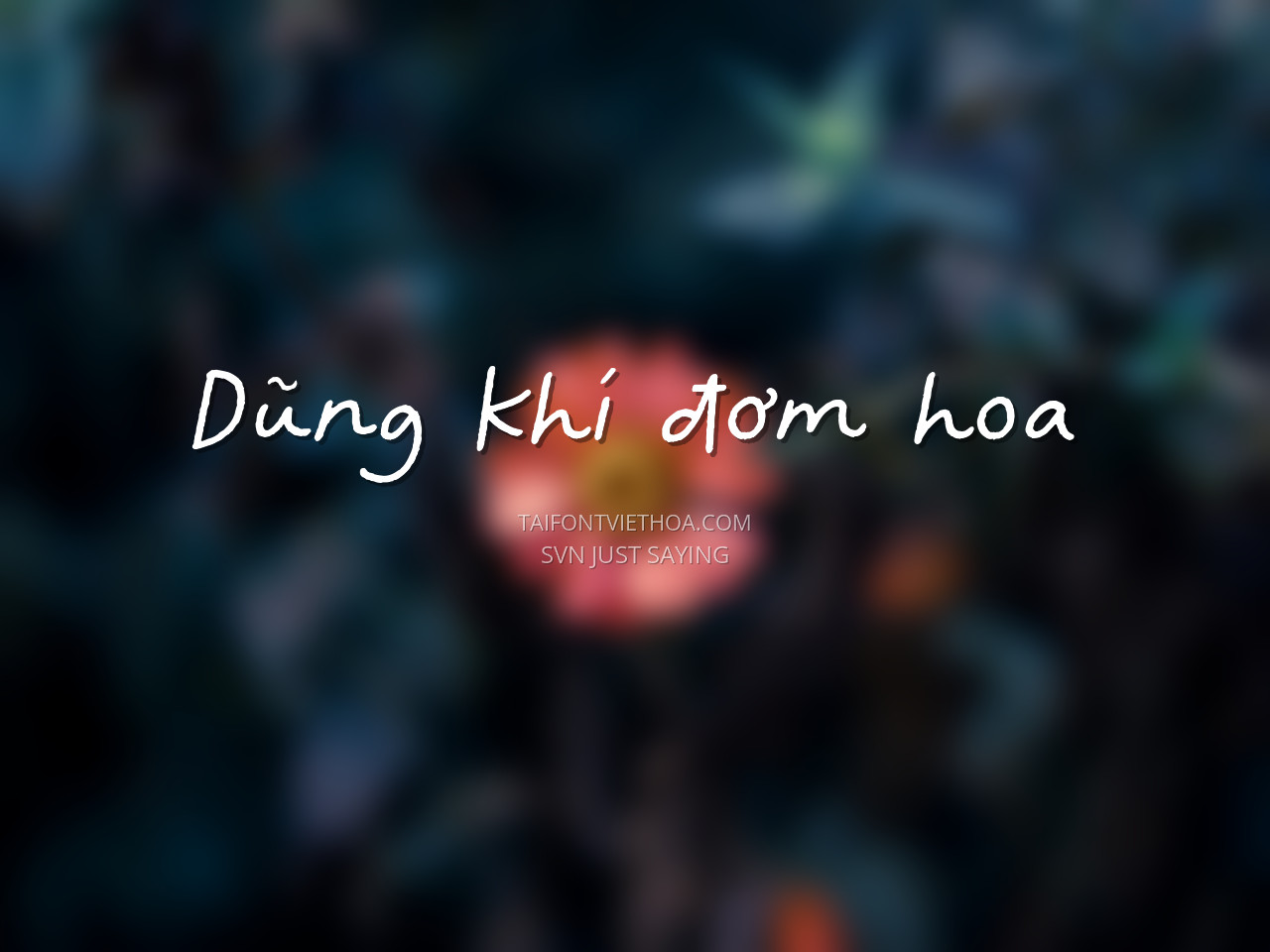
Giới thiệu về font SVN Just Saying – Kiểu chữ viết tay cá tính, năng động và trẻ trung
SVN Just Saying là phiên bản Việt hóa của font Just Saying – một kiểu chữ handwritten mang phong cách trẻ trung, năng động và đầy cá tính. Font được thiết kế với các nét chữ mềm mại, linh hoạt và đầy biểu cảm, tạo cảm giác gần gũi và thân thiện, rất phù hợp cho các dự án thiết kế thiệp mời, lời chúc, bao bì sản phẩm và các thiết kế sáng tạo mang phong cách hiện đại.
Phiên bản Việt hóa của SVN Just Saying đã được Taifontviethoa.comchăm chút kỹ lưỡng, hỗ trợ đầy đủ dấu tiếng Việt cùng hơn 60 ngôn ngữ khác. Font giữ nguyên nét mềm mại và biểu cảm của bản gốc, giúp các nhà thiết kế dễ dàng áp dụng trong nhiều dự án sáng tạo với phong cách trẻ trung, hiện đại và cá tính.
Thiết kế viết tay linh hoạt – Lý tưởng cho thiệp mời và branding cá nhân
SVN Just Saying sở hữu các nét chữ mảnh mai, mềm mại với độ nghiêng vừa phải và các ligature tinh tế, tạo nên sự hài hòa và tự nhiên trong tổng thể thiết kế. Font mang lại cảm giác sinh động, thân thiện và rất phù hợp cho tiêu đề, logo, bao bì hoặc các phần thiết kế cần điểm nhấn mềm mại và cá tính.
Ứng dụng lý tưởng: thiệp cưới, thiệp mời, logo thương hiệu trẻ trung, bao bì sản phẩm, bìa sách nghệ thuật, poster sự kiện và các dự án sáng tạo cần phong cách năng động, trẻ trung và cá tính. Ngành nghề phù hợp: cưới hỏi, mỹ phẩm, thời trang, nghệ thuật, truyền thông sáng tạo và các thương hiệu định vị theo phong cách hiện đại, năng động.